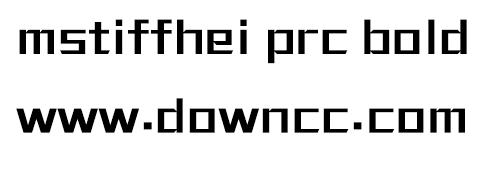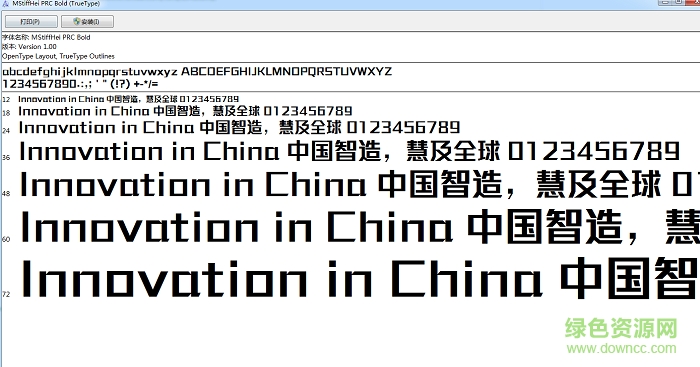
mstiffheiprc bold字體是一款整齊美觀的蒙納字體,這款字體結(jié)構(gòu)工整有序,筆畫銳利,線條筆直,可以用于辦公文檔、廣告設(shè)計、圖文排版等方面,需要的朋友趕緊來綠色資源網(wǎng)下載吧!
是一款無線襯托的裝飾體,應(yīng)用性強(qiáng),可以拉伸使用,沒有弧線,線條富有節(jié)奏與靈氣,灰度均勻,穿插合理,具有設(shè)計感與現(xiàn)代感,橫豎的筆畫對比強(qiáng)烈,突出全新的筆畫特征。